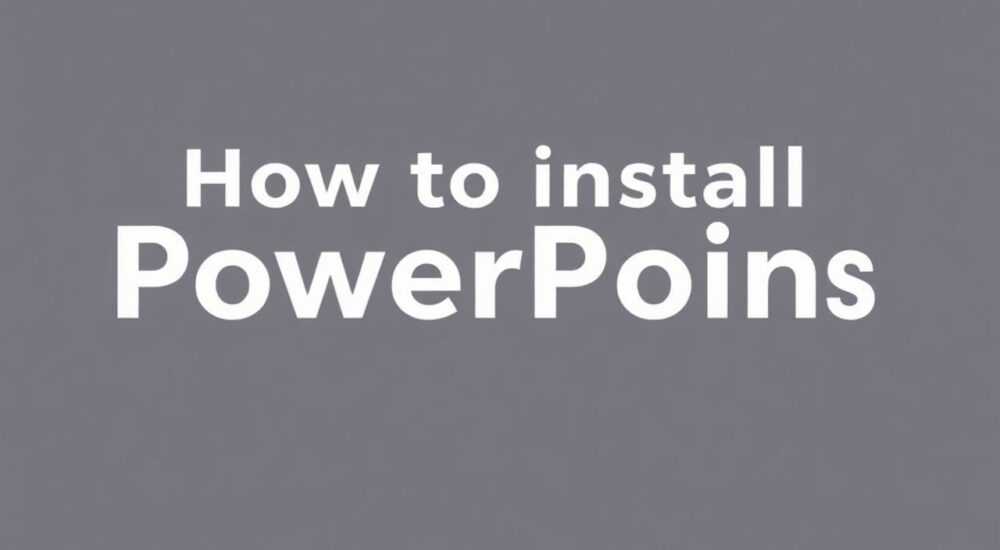
Как установить шрифт на powerpoint
Установка шрифтов в PowerPoint — простая, но важная задача для создания презентаций с уникальным стилем и профессиональным внешним видом. Многие пользователи сталкиваются с проблемой: шаблон требует определённый шрифт, которого нет в системе, или при переносе файла на другой компьютер текст отображается некорректно. Решение — правильно установить нужный шрифт и интегрировать его в PowerPoint, чтобы он корректно работал как на вашем, так и на чужом устройстве.
Чтобы использовать новый шрифт в PowerPoint, его нужно установить в операционную систему. После установки шрифт автоматически появится в списке доступных. Для надёжности сохраняйте файлы с встроенной копией шрифтов или конвертируйте текст в изображения.
Как установить шрифт в Windows для PowerPoint
Установка шрифта в Windows — это стандартная процедура, которая одинаково работает для всех программ, включая Microsoft PowerPoint. Шрифты в формате TTF (TrueType Font) или OTF (OpenType Font) легко добавляются в систему через Панель управления или проводник.
Первым делом найдите нужный шрифт. Его можно скачать с проверенных ресурсов, таких как Google Fonts, DaFont, FontSpace или Adobe Fonts. Убедитесь, что вы используете лицензионный файл — бесплатные шрифты должны быть разрешены к использованию в коммерческих целях, если вы готовите презентации для бизнеса.
Для установки выполните следующие шаги:
1. Скачайте архив с шрифтом и распакуйте его.
2. Найдите файл с расширением .ttf или .otf.
3. Щёлкните по нему правой кнопкой мыши и выберите «Установить».
4. Дождитесь завершения процесса.
После установки шрифт будет доступен во всех приложениях, включая PowerPoint. Чтобы убедиться, что всё прошло успешно, откройте любой документ Word или PowerPoint и проверьте список шрифтов в разделе «Главная» → «Шрифт».
Полезно знать: Если шрифт не появился в списке, перезапустите PowerPoint. Иногда программа не обновляет список шрифтов без перезагрузки.
Если вы работаете в системе без прав администратора, стандартный способ может не сработать. В этом случае можно вручную скопировать файл шрифта в папку C:WindowsFonts. Windows автоматически распознает его и установит. Этот метод особенно полезен в офисной среде, где доступ к системным настройкам ограничен.
Проверка совместимости шрифтов
Не все шрифты подходят для презентаций. Некоторые слишком декоративные, другие плохо читаются на экране. Перед массовым использованием протестируйте шрифт на разных слайдах: заголовках, основного текста и мелких подписях.
Критерий
Подходит
Не подходит
Читаемость
Простые, без засечек (например, Roboto)
Рукописные, искажённые формы
Размер файла
Меньше 100 КБ
Больше 500 КБ (замедляет загрузку)
Установка шрифтов на Mac: пошаговая инструкция
На macOS процесс установки немного отличается, но остаётся простым. Apple предоставляет встроенное приложение «Font Book», которое управляет всеми шрифтами системы.
Чтобы установить шрифт:
1. Скачайте файл шрифта (.ttf, .otf).
2. Дважды щёлкните по нему — система предложит открыть в «Font Book».
3. Нажмите «Установить шрифт».
4. Дождитесь появления сообщения об успешной установке.
После этого шрифт становится доступен в PowerPoint и других приложениях. Если вы используете Microsoft Office для Mac, рекомендуется перезапустить программу, чтобы обновить список шрифтов.
«Font Book позволяет создавать коллекции шрифтов — например, “Презентации” или “Заголовки”. Это помогает быстро находить нужные стили при работе над проектами.» — Александра Левина, дизайнер UX/UI, 8 лет опыта
В отличие от Windows, на Mac возможны конфликты версий шрифтов. Например, если у вас уже установлен Arial, но вы пытаетесь добавить модифицированную версию, система может игнорировать новую. В этом случае Font Book покажет предупреждение. Рекомендуется удалить старую версию перед установкой новой.
Где хранятся шрифты на Mac?
Файлы шрифтов находятся в папке /Library/Fonts (для всех пользователей) или ~/Library/Fonts (для текущего пользователя). Вы можете вручную скопировать туда файлы, и они будут доступны в системе. Однако использование Font Book предпочтительнее — оно обеспечивает корректную регистрацию и проверку целостности.
Как использовать установленные шрифты в PowerPoint
После установки шрифта в системе он автоматически появляется в списке шрифтов PowerPoint. Откройте программу, создайте или откройте существующую презентацию, выделите текст и выберите нужный шрифт из выпадающего меню.
Для удобства можно настроить шрифт по умолчанию:
1. Выделите текст с нужным начертанием.
2. Щёлкните правой кнопкой мыши и выберите «Шрифт по умолчанию».
3. Подтвердите изменение для всех новых слайдов.
PowerPoint запомнит выбор и будет использовать его при создании новых объектов. Однако будьте осторожны: не все шрифты поддерживают все начертания (жирный, курсив, светлый). Если выбранный шрифт не имеет жирной версии, PowerPoint может имитировать её, что приведёт к снижению качества отображения.